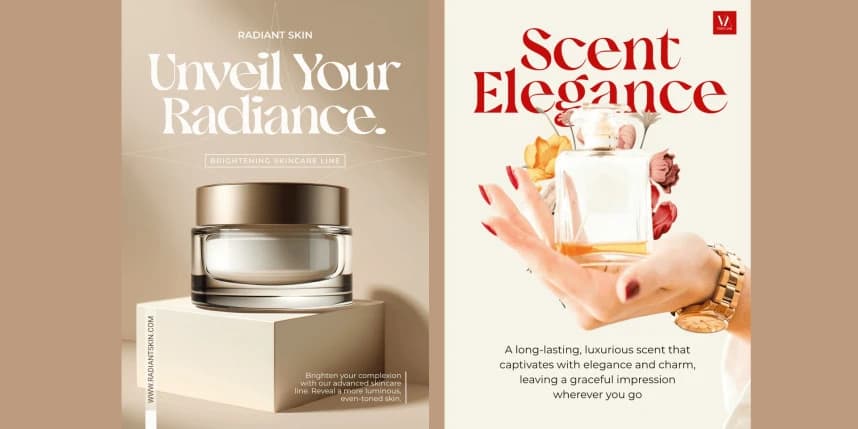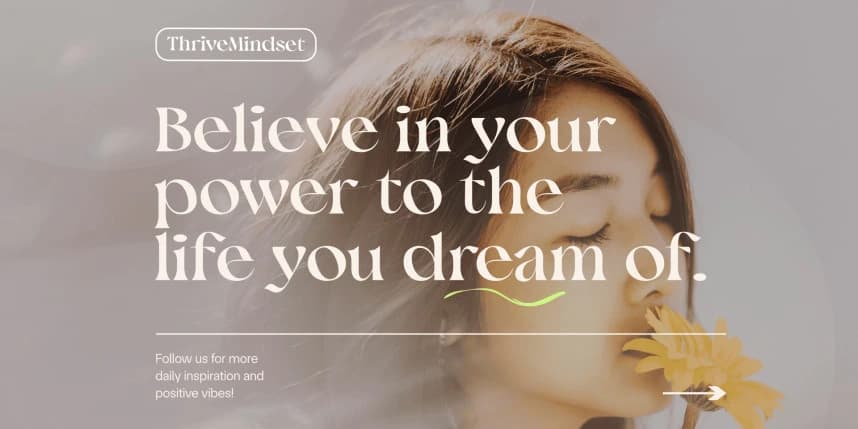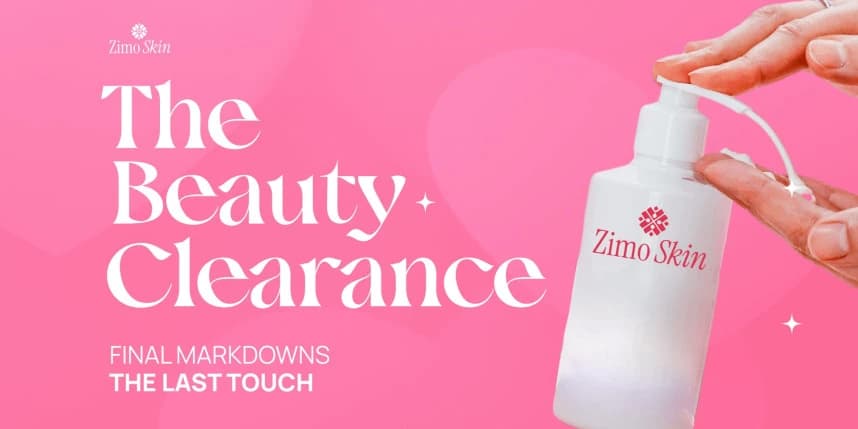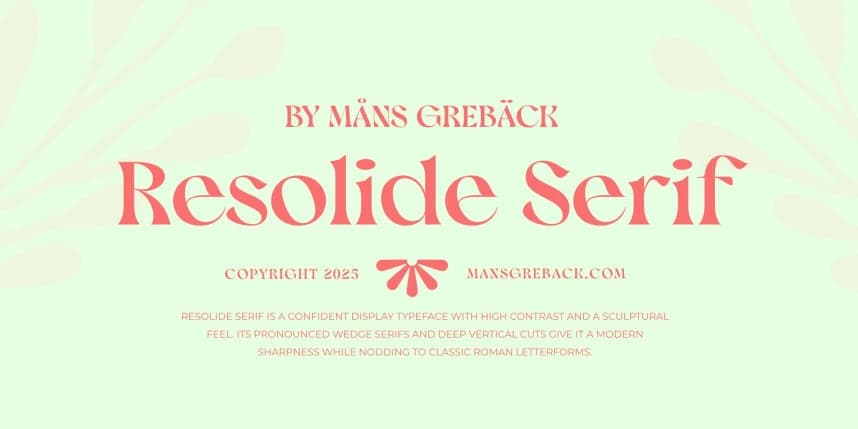
Resolide Serif Font
Resolide Serif Font, yüksek kontrastlı ve heykelsi bir his veren özgüvenli bir gösteri yazı tipidir. Belirgin kama şeklindeki serifler ve derin dikey kesikler ona modern bir keskinlik kazandırırken, klasik Roma harf biçimlerine selam durur. Biçimlerinin ritmi gölge ile ışık arasında dans eder ve dra
Resolide Serif Font, yüksek kontrastlı ve heykelsi bir his veren kendine güvenen bir gösterişli yazı tipidir. Belirgin kama biçimli serifler ve derin düşey kesikler ona modern bir keskinlik kazandırır ve klasik Roma yazı karakterlerine selam eder. Biçimlerinin ritmi gölge ile ışık arasında dans eder; özellikle büyük boyutlarda dramatik bir etkileşim yaratır.